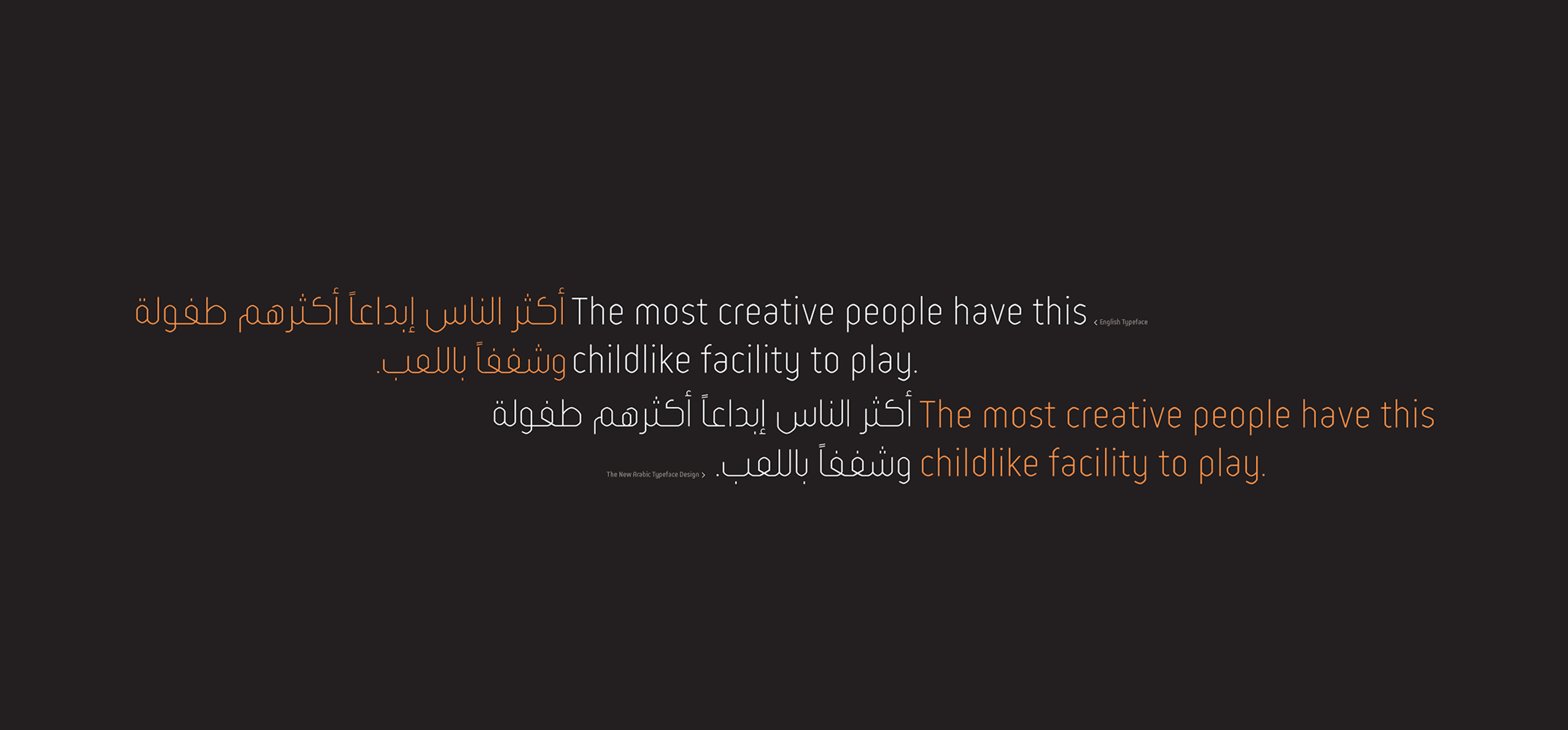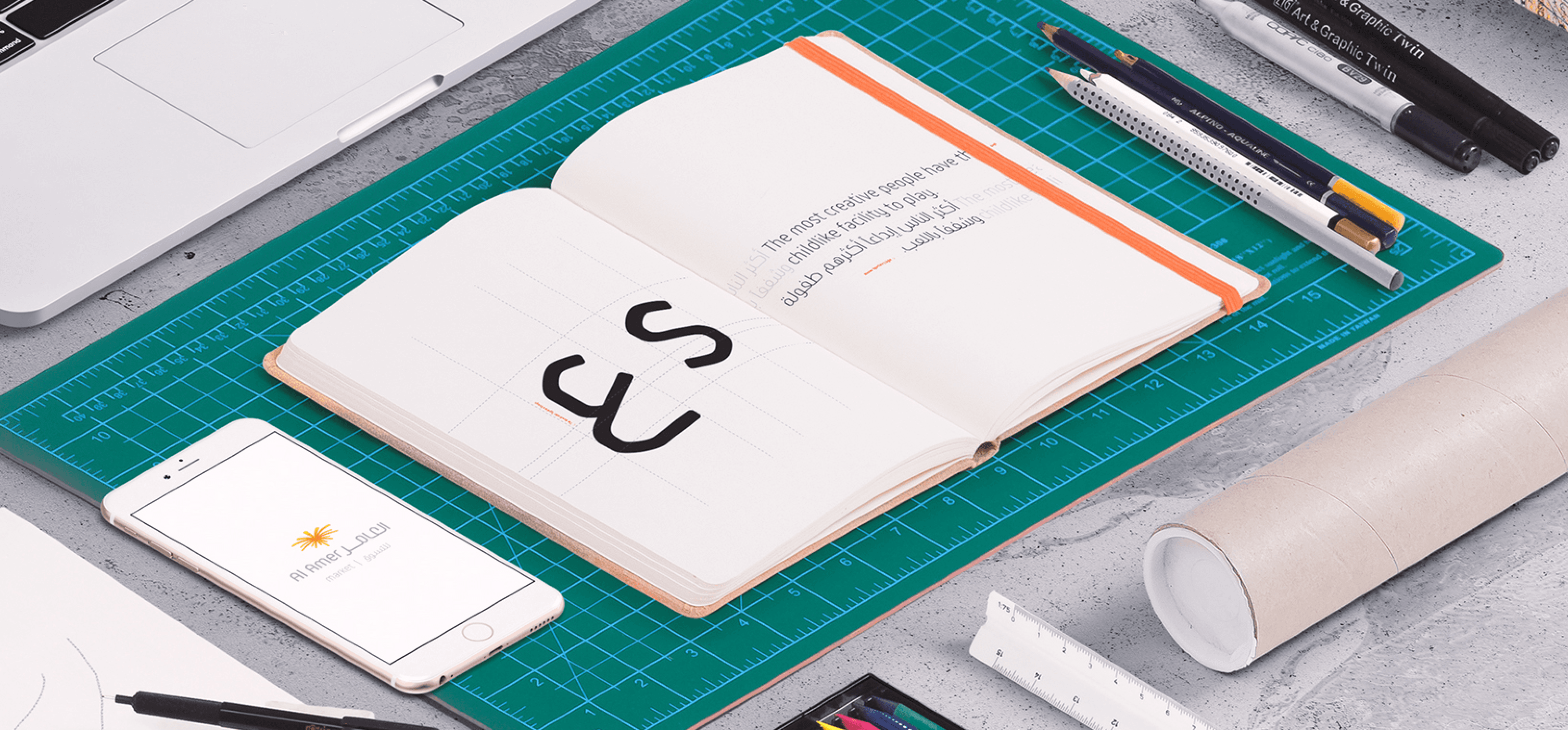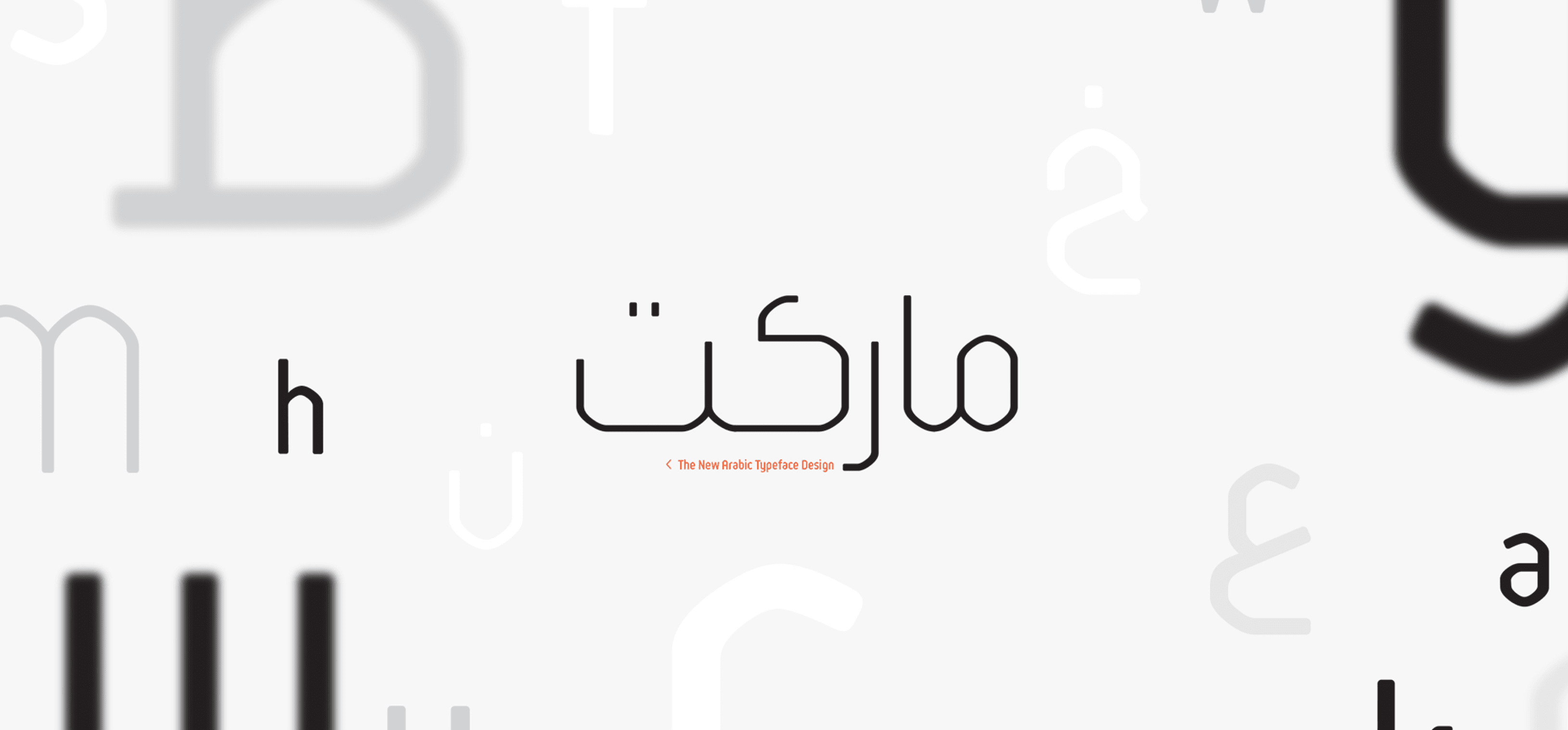
قمنا بتصميم خط جديد وفريد لعميلنا، كبديل للخطوط التقليدية، مستوحى من هوية علامتهم التجارية.
يتميز الخط بانحناءاته اللطيفة غير الحادة، مما يجعله أكثر سهولة في الاستخدام والتطوير. هذه الخصائص تجعل منه خيارًا مناسبًا لعلامة Alammer، حيث يجمع بين التميز والبساطة في آن واحد.
قمنا بتصميم خط جديد وفريد لعميلنا، كبديل للخطوط التقليدية، مستوحى من هوية علامتهم التجارية.
يتميز الخط بانحناءاته اللطيفة غير الحادة، مما يجعله أكثر سهولة في الاستخدام والتطوير. هذه الخصائص تجعل منه خيارًا مناسبًا لعلامة Alammer، حيث يجمع بين التميز والبساطة في آن واحد.
قمنا بتصميم خط جديد وفريد لعميلنا، كبديل للخطوط التقليدية، مستوحى من هوية علامتهم التجارية.
يتميز الخط بانحناءاته اللطيفة غير الحادة، مما يجعله أكثر سهولة في الاستخدام والتطوير. هذه الخصائص تجعل منه خيارًا مناسبًا لعلامة Alammer، حيث يجمع بين التميز والبساطة في آن واحد.